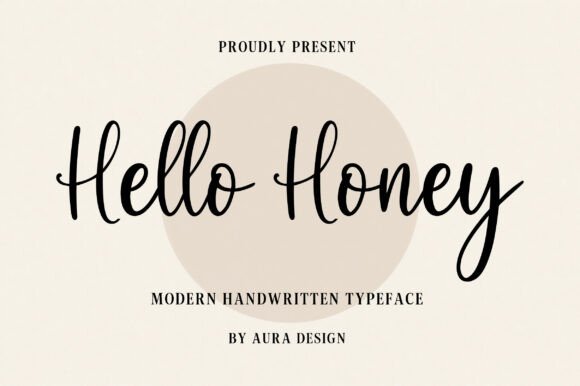
Hello Honey
Encontrar os elementos de design certos pode ser um desafio, mas Hello Honey oferece uma coleção excepcional que eleva o seu trabalho instantaneamente.
Trabalhado com precisão, Hello Honey fornece vetores limpos, tipografia suave e uma licença comercial para sua tranquilidade.